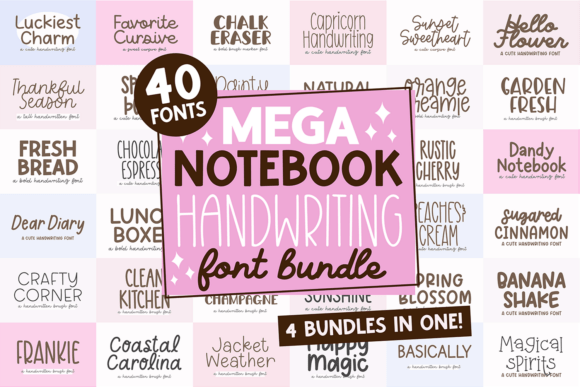
Mega Notebook Handwriting Bundle
Wenn Sie nach hochwertigen Assets wie Mega Notebook Handwriting Bundle suchen, ist dieses Premium-Paket eine fantastische Wahl für Ihre kreativen Projekte.
Egal, ob Sie POD-Produkte (Print on Demand), Hochzeitseinladungen oder Social-Media-Grafiken erstellen, Mega Notebook Handwriting Bundle ist die ideale Wahl.